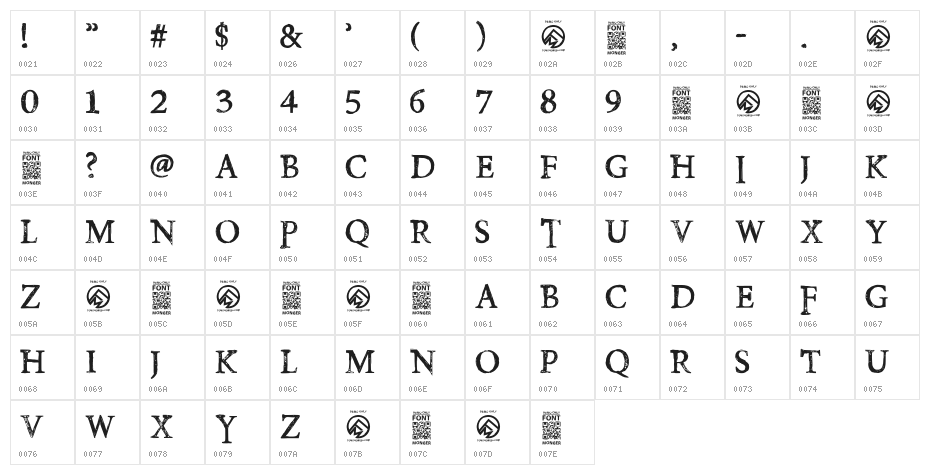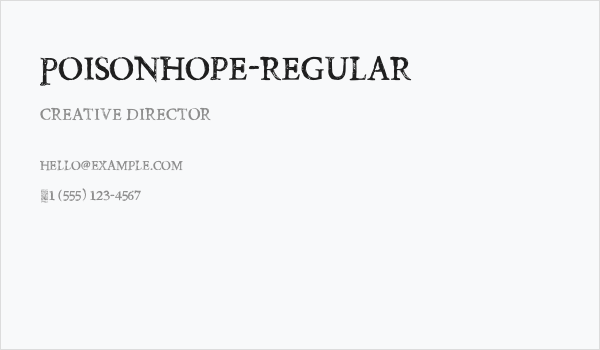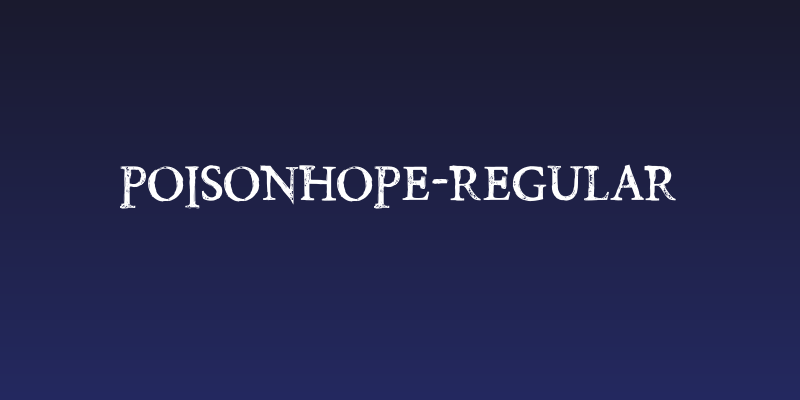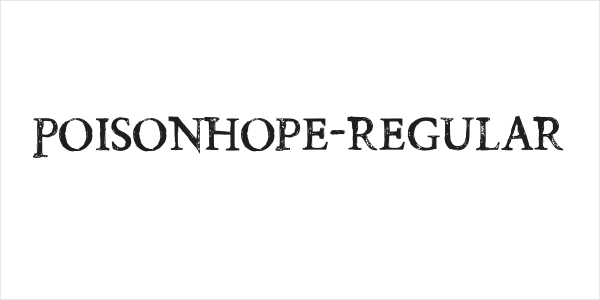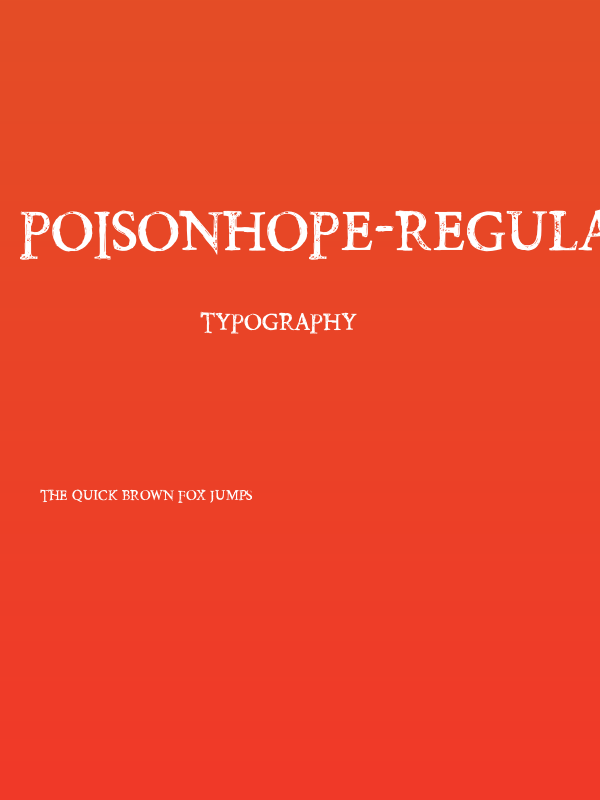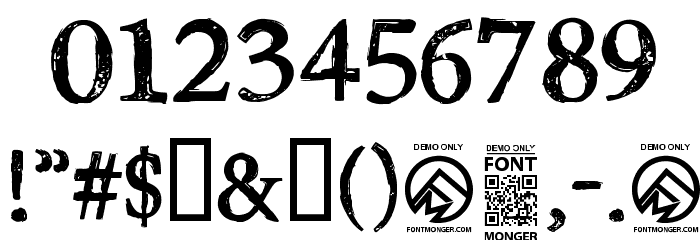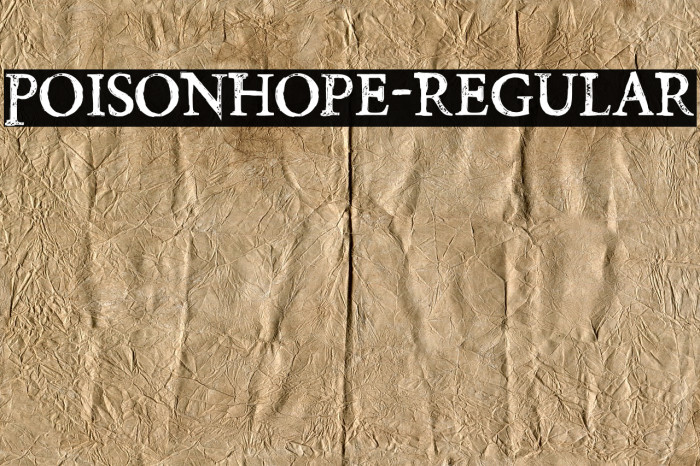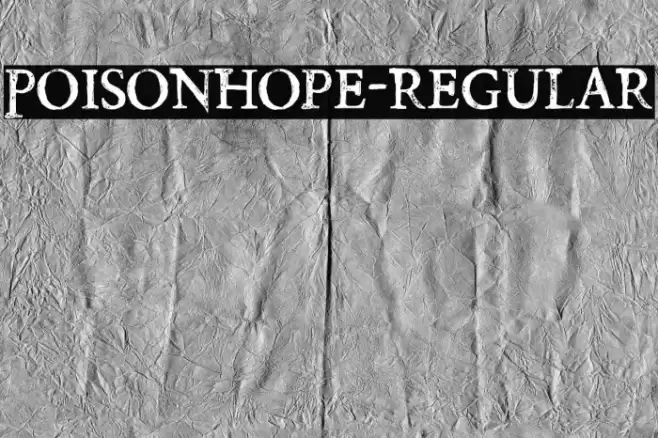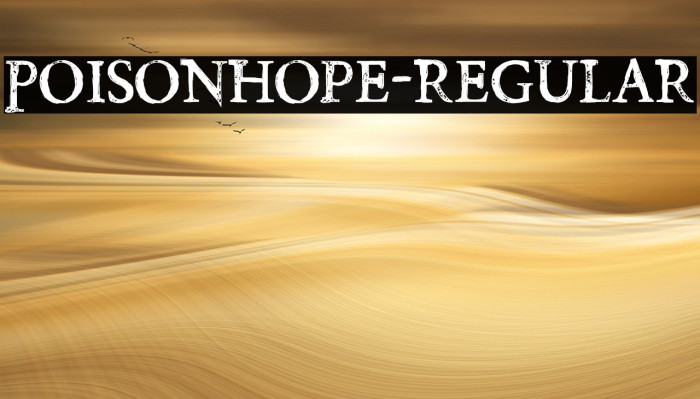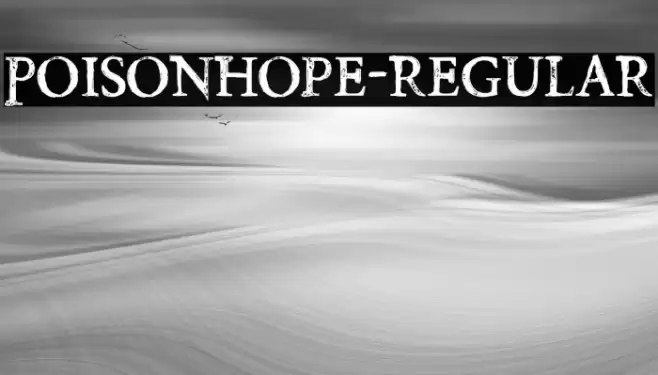
PoisonHope-Regular Font
✎ Distorted Eroded
| الفئات | Distorted Eroded |
| النمط العام | Vintage, Edgy |
| مشاريع مقترحة | Ideal for music album covers, posters, branding for edgy or alternative products, and any design needing a vintage, rugged look. |